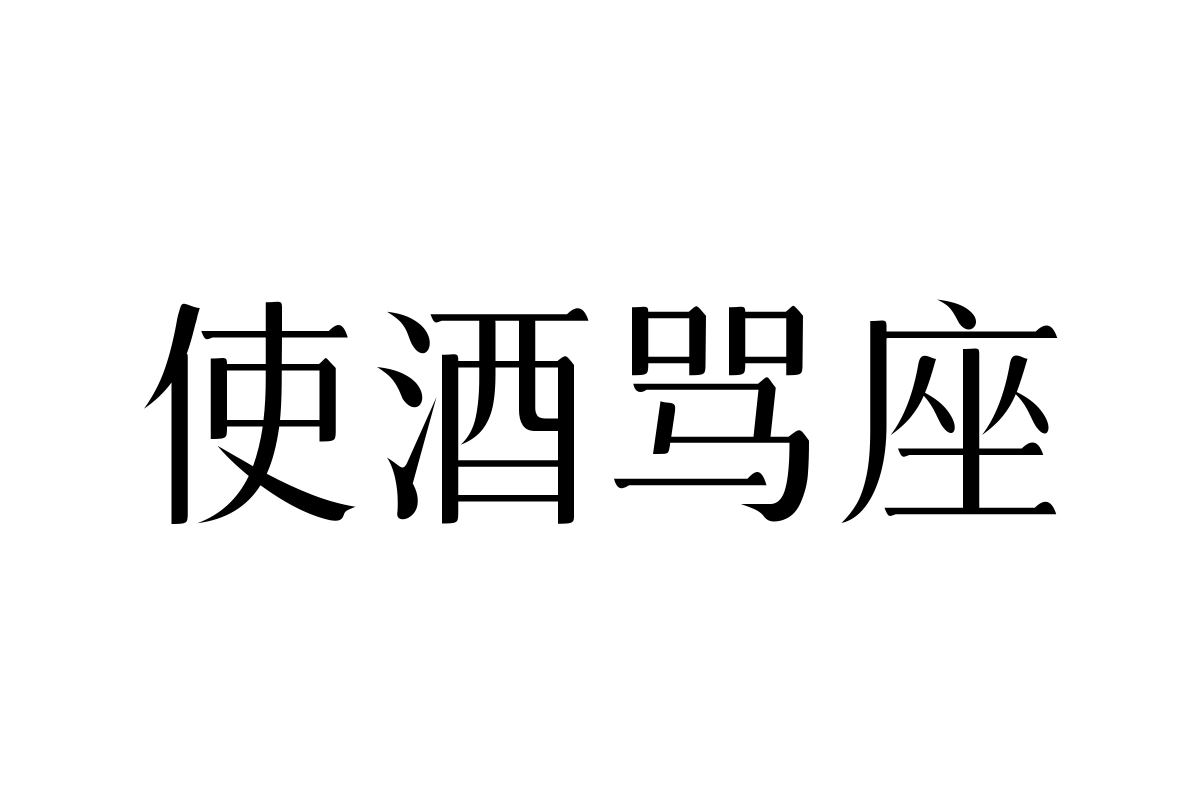
三极清宋简体字体是一款由三极公司开发的中文简体字体,主要用于书籍、报纸、杂志等印刷品的排版。这款字体的特点在于其字形简洁,笔画流畅,易于阅读,同时保留了一定的传统书法韵味,使得整体视觉效果更加美观大方。
三极清宋简体字体采用了现代设计手法,对传统的宋体进行了简化和优化,使其更加符合现代人的审美需求。在字形上,该字体保持了宋体的基本结构,但通过简化笔画和调整字间距,使得整体看起来更加清晰易读。此外,三极清宋简体字体还注重字体的可读性,通过调整字重和行距,使得文字在页面上的分布更加均匀,提高了阅读体验。
总的来说,三极清宋简体字体是一款适用于各种印刷品的中文简体字体,具有简洁、易读、美观等特点,是设计师和印刷工作者的首选字体之一。